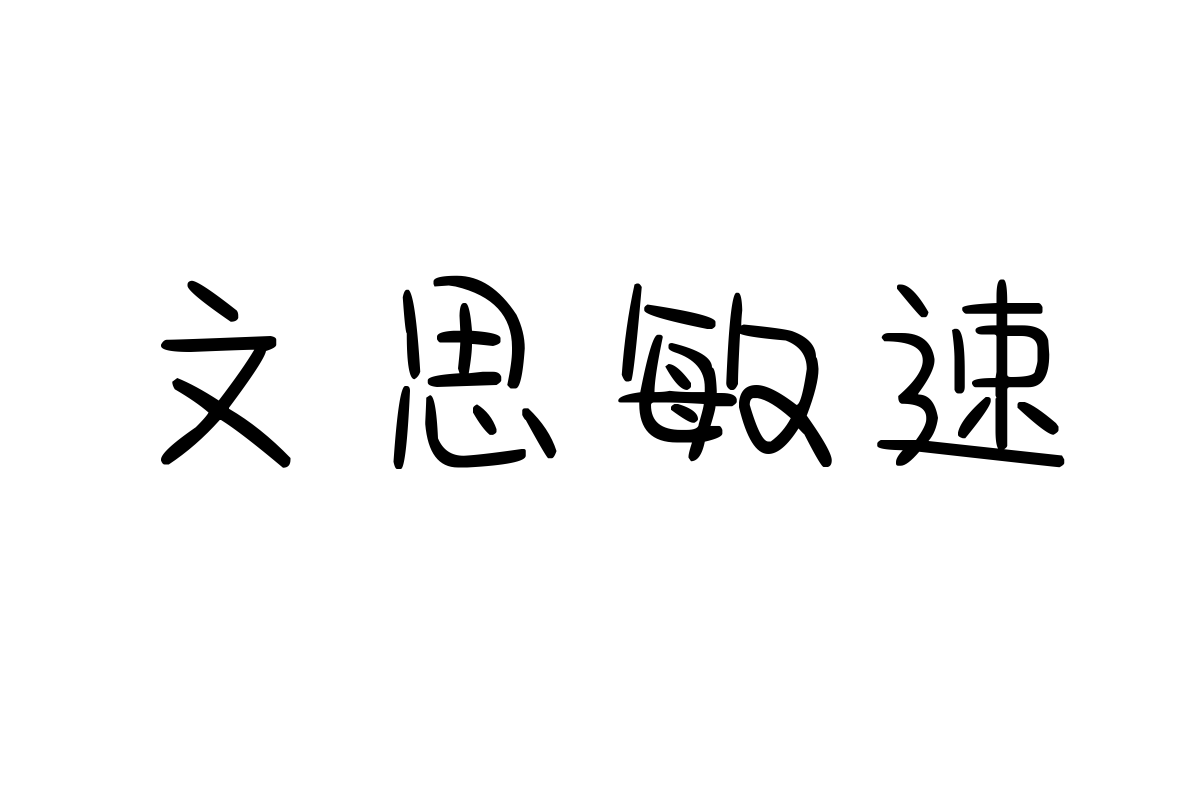
也字工厂杰瑞手迹是一款独特的字体,它融合了传统书法的韵味和现代设计的简洁线条。这款字体具有以下特点:
1. 独特性:也字工厂杰瑞手迹采用了独特的手写风格,将传统的书法艺术与现代设计元素相结合,创造出一种全新的视觉体验。
2. 可读性:虽然采用了手写风格,但这款字体仍然保持了较高的可读性,适合用于各种文字排版场景,如标题、正文、广告等。
3. 个性化:也字工厂杰瑞手迹可以根据用户的需求进行个性化定制,满足不同场合、不同风格的设计需求。
总之,也字工厂杰瑞手迹是一款集传统书法韵味与现代设计简洁线条于一体的字体,适用于各种文字排版场景,具有较高的可读性和个性化特点。